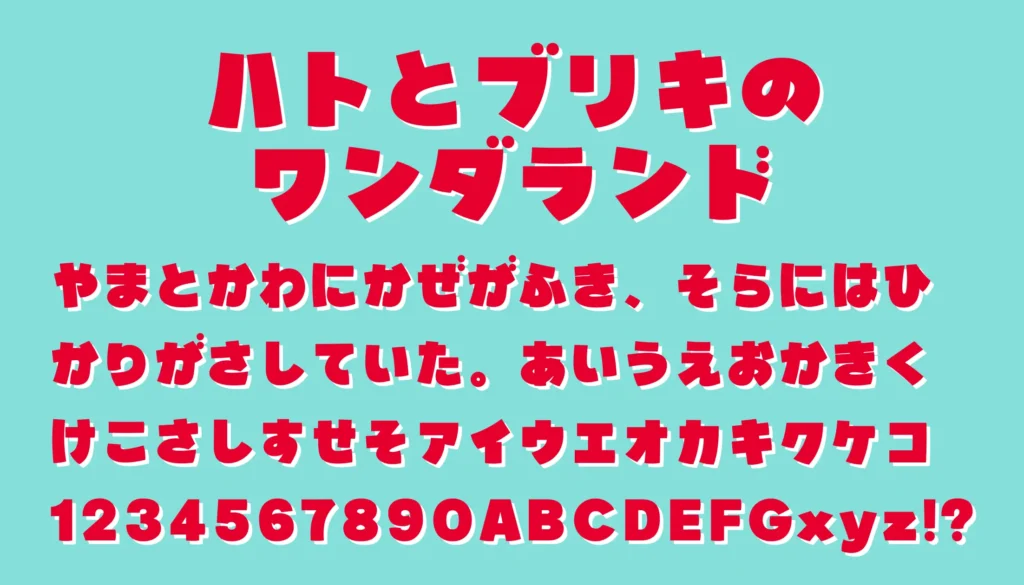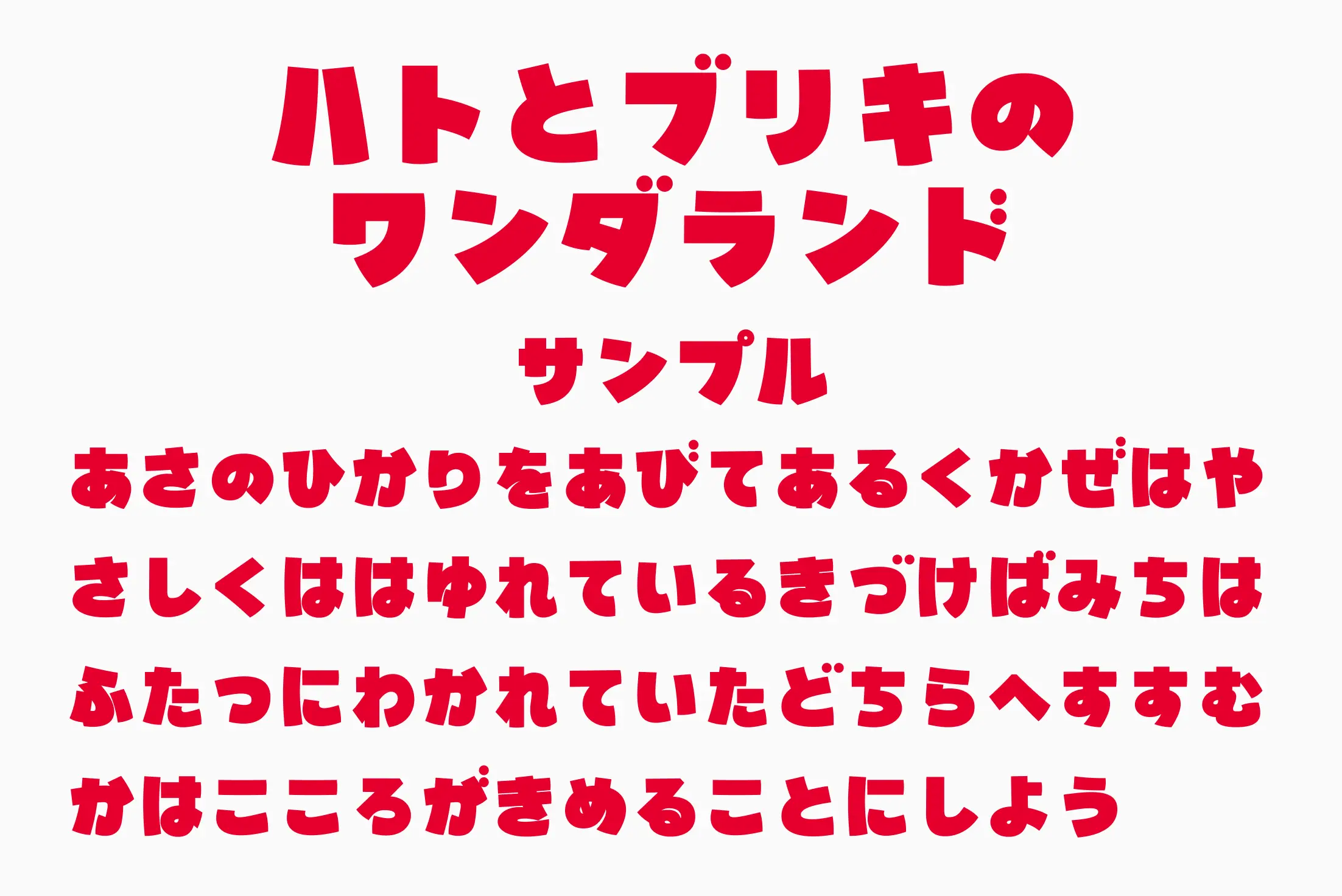
極太でレトロ感たっぷりなのに、どこか抜け感もある“懐かしポップ”なデザインフォント。文字ごとに少し傾きやリズム感が違っていて、まるで昭和のおもちゃ箱や看板をそのまま切り取ったような遊び心があります。タイトルロゴや動画サムネ、アイキャッチに使うと一気に世界観が完成するタイプで、特に“元気・レトロ・かわいい”を出したいデザインと相性抜群。丸みのあるフォルムのおかげで圧が強すぎず、親しみやすさも感じられるのが魅力です。
鳩とブリキのワンダランド
| 収録文字 | ひらがな・カタカナ・英字・数字・記号 |